18 polices professionnelles et d'entreprise de première classe pour 2023
Publié: 2023-01-18L'image de marque fait partie intégrante de tout site Web, mais surtout pour les entreprises. Une partie de cette image de marque est la façon dont votre texte actuel. Cela peut être une décision difficile, car il y a tellement de polices d'entreprise et d'entreprise disponibles. Cependant, cela signifie que vous pourrez trouver quelque chose qui vous convient.
La portée des polices commerciales et d'entreprise est large, en raison de différents objectifs. Par exemple, certains conviennent aux titres, d'autres sont parfaits pour l'image de marque de l'entreprise en général, tandis que d'autres aideront votre corps de texte à briller.
Pour cet article, nous allons rassembler certaines des meilleures polices commerciales et d'entreprise que nous pouvons trouver. Avant cela cependant, nous allons vous donner des conseils sur la façon de choisir la bonne police commerciale et d'entreprise pour vos besoins.
Comment choisir une police d'entreprise et d'entreprise
Il convient de noter que même si nous utilisons le terme "police" ici, notre liste contient des "polices de caractères". La principale différence est qu'une police de caractères contient un certain nombre de polices différentes (comme en gras ou en italique). Même ainsi, certaines des entrées de cette liste sont également des polices réelles.
Quant à savoir comment en choisir un, il est important de déterminer vos besoins. Si vous voulez une police pour votre logo, cela dictera ce que vous recherchez. En revanche, si votre site a un design axé sur la typographie, la clarté et la lisibilité seront essentielles. Il y a trois principes clés que vous voudrez considérer :
- Assurez-vous de bien comprendre la personnalité et le public de votre marque. Vous pouvez créer une liste de mots avec lesquels travailler. Cela vous aidera à affiner les types de polices à rechercher.
- Certaines polices évoquent des émotions, tout comme les couleurs. En tant que tel, prenez également le temps de rechercher des personnalités de police.
- Réfléchissez aux autres polices que vous utiliserez sur votre site. Pour cette raison, la façon dont une police s'associe à d'autres est importante pour votre image de marque globale et la convivialité de votre site.
Une fois que vous aurez compris les trois éléments, vous en aurez assez pour commencer à consulter notre liste suivante de polices commerciales et d'entreprise.
18 polices professionnelles et d'entreprise de première classe pour 2023
Nous avons une grande liste de polices d'entreprise et d'entreprise parmi lesquelles choisir, nous ne perdrons donc pas de temps pour accéder à la liste. Cependant, notez que nous ne les présentons pas dans un ordre particulier. Cela signifie que vous voudrez étudier chacun d'entre eux pour voir s'il correspond aux besoins de votre entreprise.
1. Magnolia
Tout d'abord, nous avons Magnolia. Bien que cela ne ressemble pas à une police d'entreprise et d'entreprise, il s'agit d'un design serif moderne qui a de nombreuses utilisations.
Par exemple, bien qu'elle ne convienne pas à tous les types d'entreprises, elle pourrait convenir comme police de titre pour les fleuristes et les entreprises féminines. Si vous souhaitez donner à votre site un aspect original et contemporain, Magnolia pourrait être une bonne option.
2. Signature commerciale
Business Signature est une autre police qui ne conviendra pas à tous les types de sites. Cependant, ce script déborde de classe. Bien sûr, cette police n'en est pas une pour votre corps de texte. Au lieu de cela, il s'assiéra dans les en-têtes, se retrouvera dans les logos et fonctionnera bien comme un texte de déclaration.
Dans l'ensemble, Business Signature vous permettra de personnaliser votre marque. Cela vous permettra de donner à votre entreprise une marque de qualité et de luxe qui en fait l'une des meilleures polices de cette liste.
3. Mislan
Nous avons un autre titre et une autre police d'affichage pour vous. Mislan projette de la puissance, et malgré son apparence, nous pensons qu'il peut bien fonctionner avec de nombreuses entreprises différentes.
La police conviendra parfaitement aux créatifs, aux sites Web à la mode, aux musiciens, etc. Même ainsi, étant donné la bonne image de marque, nous pouvons voir Mislan sur les sites d'avocats et dans d'autres situations où une police telle qu'Impact ne suffit pas. Dans l'ensemble, Mislan est plus polyvalent qu'il n'y paraît.
4. Codec Pro
Codec Pro est la première police sans empattement de notre liste. Parce qu'elle ne se démarque pas (contrairement à beaucoup d'autres polices d'entreprise et d'entreprise ici), vous pouvez utiliser cette police presque n'importe où sur votre site.
Par exemple, il est suffisamment volumineux pour être utilisé comme police d'affichage. En revanche, des poids plus légers seront parfaits pour un corps de texte lisible. La police de caractères dans son ensemble est fiable, ce qui peut donner à toute entreprise un air de confiance et d'autorité.
Codec Pro coûte 175 $ pour une licence de bureau et augmente en fonction des pages vues pour une licence de police Web.
5. Livraison délicieuse
Malgré son nom, Yummy Delivery n'est pas seulement destiné aux sites de livraison et aux entreprises. C'est amusant et décalé, et ne se prend pas trop au sérieux. Nous le considérons comme faisant partie d'une feuille de conception de marque d'entreprise de garde d'enfants ou d'une entreprise de boissons santé. Cependant, cela pourrait convenir à toute entreprise qui valorise l'informalité.
La police de caractères comprend quatre polices différentes, mais ce sera mieux comme texte d'affichage. Même ainsi, à des tailles plus petites, Yummy Delivery est toujours lisible, ce qui en fait une bonne police de caractères de titre général.
6. Planex
Planex est une police super puissante idéale pour les logos et les grands écrans. Le lettrage est grand, ce qui signifie qu'il peut ne pas être lisible dans les petites tailles.
Cette police donnera à votre entreprise un air de fiabilité et de confiance. C'est une conception sérieuse, donc les sociétés et les grandes entreprises en bénéficieront. Les avocats, les fabricants, les entrepreneurs et bien d'autres conviendront à Planex. Même ainsi, il pourrait également être utilisé pour une entreprise créative dans le bon contexte.
7. Daltons
Les polices et les polices de caractères subtiles sont toujours gagnantes. Ils offrent un design lisible et fiable, mais ont suffisamment de différence pour se sentir frais pour le lecteur. Dalton en est un excellent exemple, bien que celui-ci ne soit pas flexible.
Vous n'obtenez que des lettres majuscules, ce qui signifie que Dalton est une police d'affichage et d'en-tête. Il dégage des vibrations élégantes, et nous pourrions le voir utilisé pour les entreprises de bijoux ou la mode.
8. Geotrica
Geotrica est une autre police de caractères sans empattement fiable et flexible. Nous aimons le mieux les polices en gras, bien que les polices régulières aient aussi leur place.
L'unique argument de vente de Geotrica est sa lisibilité. Il chevauche une ligne à espacement fixe sans être ce genre de police de caractères. Cela le rend idéal sur tout votre site. Avec la bonne feuille de conception, Geotrica peut faire partie de l'image de marque de presque tous les créneaux commerciaux.
9. Holygrave
Voici un script de pinceau pour les entreprises créatives. Holygrave fonctionnera bien pour les musiciens, les salons de tatouage et peut-être même les entreprises de design.
Bien sûr, ce ne sera pas une police que vous utiliserez pour un cabinet médical. Cependant, un avantage majeur ici est la capacité d'adaptation de Holygrave. Cela pourrait faire partie de vos médias sociaux et d'autres marques hors site, ce qui est un avantage si vous comptez sur différents canaux pour commercialiser votre entreprise.
10. Anisalie
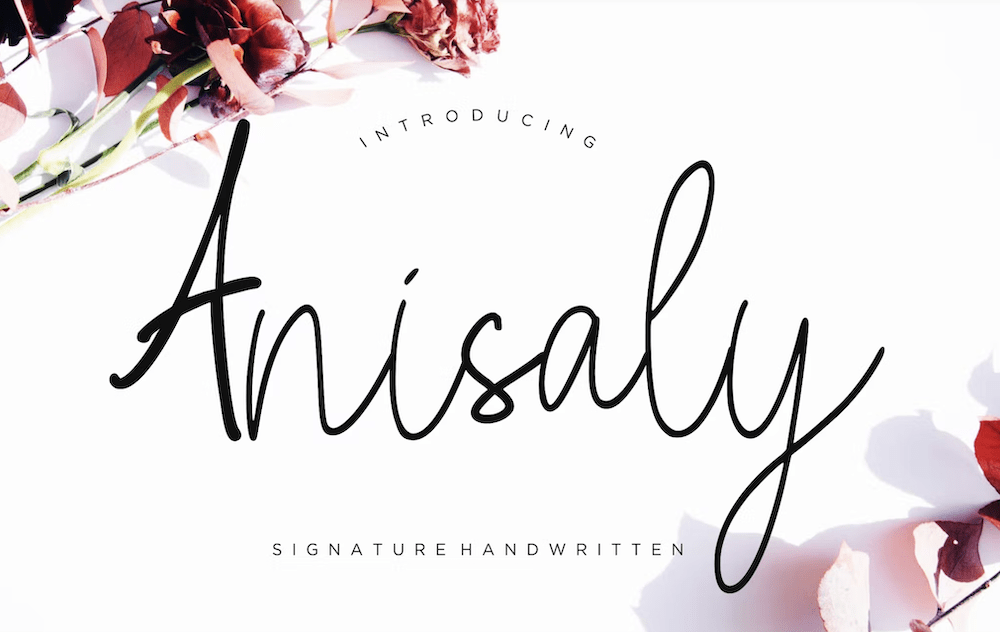
Tout comme Business Signature, Anisaly est un script d'écriture manuscrite qui vous permet de développer une image de marque personnelle. Cela ressemble à une écriture naturelle, ce qui est positif. Vous pouvez donner l'impression que votre site provient directement du créateur, plutôt que d'utiliser un rapide "gribouillis" pour désigner une signature.
Cependant, contrairement à Business Signature, Anisaly est plus féminine. En tant que tels, ces types d'entreprises conviendront à cette police plus que d'autres.
11. Élément
Les produits de grande valeur dépendent de l'image de marque pour réussir. Element est une police sans empattement et en blocs qui crie un goût riche.
Il s'agit d'une police d'affichage qui fonctionne pour l'image de marque du produit, bien que dans différents contextes, elle puisse également vous donner une sensation nostalgique. Element a des traits de design cool et de l'élégance. Les entreprises masculines graviteront vers cette police – vêtements, véhicules, articles de luxe, soins personnels, etc.
12. Lion Arrondi Pro
Nous aurions pu mettre n'importe laquelle des options de police de caractères Leo sur cette liste, car elles ont toutes l'air fantastiques. Cependant, Leo Rounded Pro obtient notre vote car il marie les types de conception formels et informels.
Il s'agit d'une police moderne qui conviendra aux grands écrans et au texte du héros. En tant que tel, vous voudrez l'associer à une autre police - Leo Sans serait parfait. La police arrondie est une police formelle pour les environnements informels - art, vêtements modernes, musique et autres activités créatives.
Leo Rounded Pro coûte 29 $ pour une licence de bureau. Cependant, les licences de polices Web commencent à partir de 100 $.
13. Versanité
À première vue, Versanity semble être une police serif adaptée aux entreprises de mode. Cependant, il peut faire plus que cela, grâce à son design sobre et élégant.
Par exemple, vous pouvez l'utiliser pour les marques de luxe, les médias et les entreprises "traditionnelles". Selon l'image de marque, l'air digne de confiance de Versanity peut également fonctionner pour les entreprises médicales et autres.
Cependant, bien qu'il y ait à la fois des lettres majuscules et minuscules, Versanity ne se lit pas trop bien dans les petites tailles. Il s'agit d'un logo et/ou d'une police d'affichage.
14. Temps des médias
Oui, c'est un dérivé du Times New Roman. Non, Media Times n'est pas une police que vous devriez rejeter d'emblée. En fait, c'est l'une des meilleures polices commerciales et d'entreprise de cette liste. Tout comme Versanity est adaptable, cette police l'est aussi.
Les entreprises de bureau considéreront Media Times, tout comme les médias, les avocats, l'éducation, la mode, les marques de luxe, etc. Vous l'utiliserez comme police d'affichage ou de titre, étant donné qu'elle ne comprend que des lettres majuscules. Dans l'ensemble, Media Times peut s'intégrer à presque toutes les marques.
15. Univa Nova
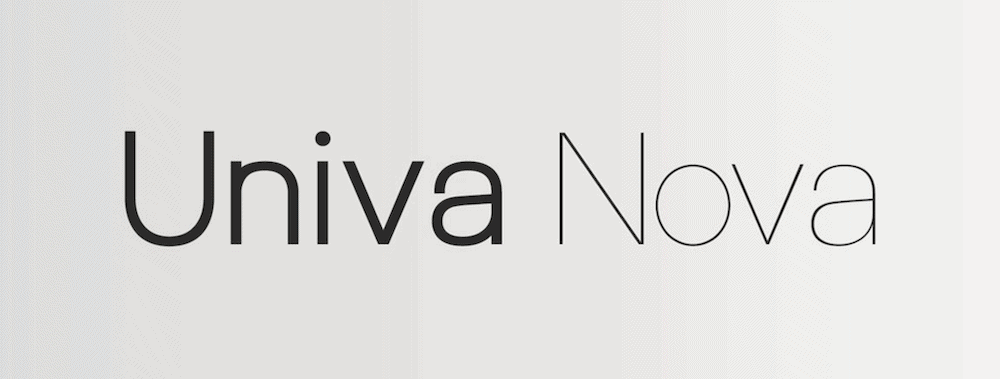
Les polices de caractères sans empattement fonctionnent souvent parce qu'elles sont minimalistes, lisibles et génériques. Bien que vous puissiez classer "générique" comme un terme négatif, pour l'image de marque, c'est parfait. Univa Nova en est un bon exemple, car il est suffisamment discret pour s'adapter à tous les aspects d'un site.
Les entreprises technologiques trouveront des qualités « Apple » dans Univa Nova, mais ce n'est pas le seul domaine qui convient. Les entreprises de mode aimeront également cette police. Partout où vous avez besoin d'un design sobre mais de qualité, Univa Nova conviendra.
Mieux encore, les licences de bureau et de police Web pour Univa Nova coûtent 39 $.
16. JUST Sans
JUST Sans fait ce qu'il dit sur la boîte. C'est une police de caractères sans empattement avec des lignes épurées, un ensemble impressionnant de poids et un design subtil.
En matière de lisibilité, JUST Sans prend le gâteau. Il est à la fois moderne et nostalgique, et conviendra à presque toutes les entreprises avec les bons choix de conception. Vous réfléchirez peut-être à deux fois avant d'utiliser JUST Sans comme police d'affichage pour un fleuriste, par exemple. Cependant, même dans ce cadre, vous pouvez l'utiliser comme corps de texte.
17. Thillik
Thillik est sans doute le domaine le plus à gauche des polices commerciales et d'entreprise de cette liste. Nous aimons ses bizarreries et comment cela peut se présenter à vos clients potentiels.
Il chevauche la frontière entre l'informel et le formel. Contrairement à Leo Rounded Pro, il s'agit d'une police informelle pour les paramètres de format. Pensez aux entreprises de livraison, aux restaurants et aux autres entreprises traditionnelles.
Il s'agit d'une autre police où ses lettres minuscules peuvent parfois être illisibles. Nous utiliserions principalement Thillik comme police d'affichage.
18. Trifélia
Si vous cherchez Versanity et Dalton mais que vous ne voulez pas payer pour un abonnement Envato Elements, Trifelia pourrait être pour vous. Nous aimons son apparence, et c'est un gagnant clair pour les entreprises de mode, de bijoux et de luxe.
Il n'y a que des lettres majuscules disponibles, ce qui signifie que Trifelia est une police d'affichage dans l'ensemble. C'est chic et élégant, et mieux encore, c'est gratuit. Cela signifie que vous pouvez le télécharger et l'essayer sans risque. Vous trouverez également une mise à niveau premium pour environ 10 $ qui comprend plus d'options de type de fichier.
En résumé
Le choix d'une police d'entreprise et d'entreprise nécessite des efforts, mais cela en vaut la peine. La bonne police de caractères peut cimenter votre marque comme une marque de confiance et peut également lui donner une certaine personnalité. Notre liste de polices d'entreprise et d'entreprise semble fournir un large éventail d'options.
Même ainsi, nous aimons JUST Sans. En effet, il peut s'intégrer à un certain nombre de types d'entreprises et d'applications différents au sein de votre image de marque. Il a suffisamment de personnalité pour fonctionner comme un logo ou un en-tête, tandis qu'une police sans empattement est idéale pour le corps du texte.